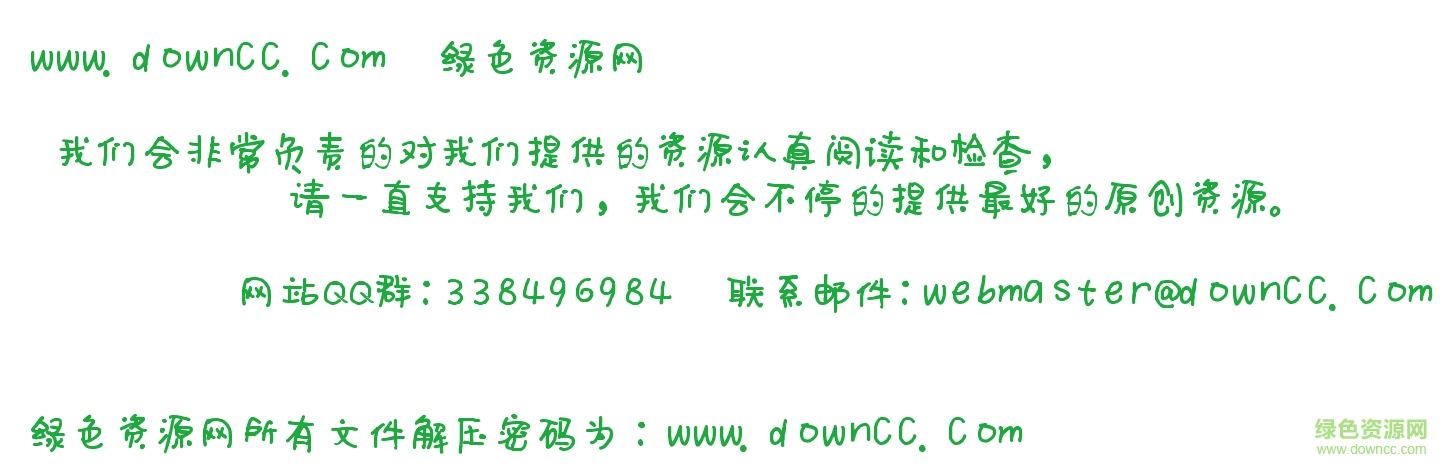
默陌歪歪體是一款字體卡通Q萌的藝術字體,有著不規(guī)整的字形和活潑有趣的外觀,充滿了童真和童趣,給你盎然生趣的愉悅體驗,綠色資源網(wǎng)誠意推薦!
默陌歪歪體是由張默模制作的新款體驗,有著獨特的卡通字體體驗,如通剛會握筆的稚童,認真的寫字,可廣泛運行于海報設計、文字印刷、廣告創(chuàng)意等行業(yè)。
默陌歪歪體是一款筆畫圓潤,結(jié)構(gòu)上松下緊的的兒童風格字體,通過正統(tǒng)書法字體間架的解構(gòu),制造一種重心不穩(wěn)定的視覺感,字體筆畫簡單稚拙,寬細一致,充分體現(xiàn)出孩童的書寫特點,適用于各種輕松活潑的媒介應用。